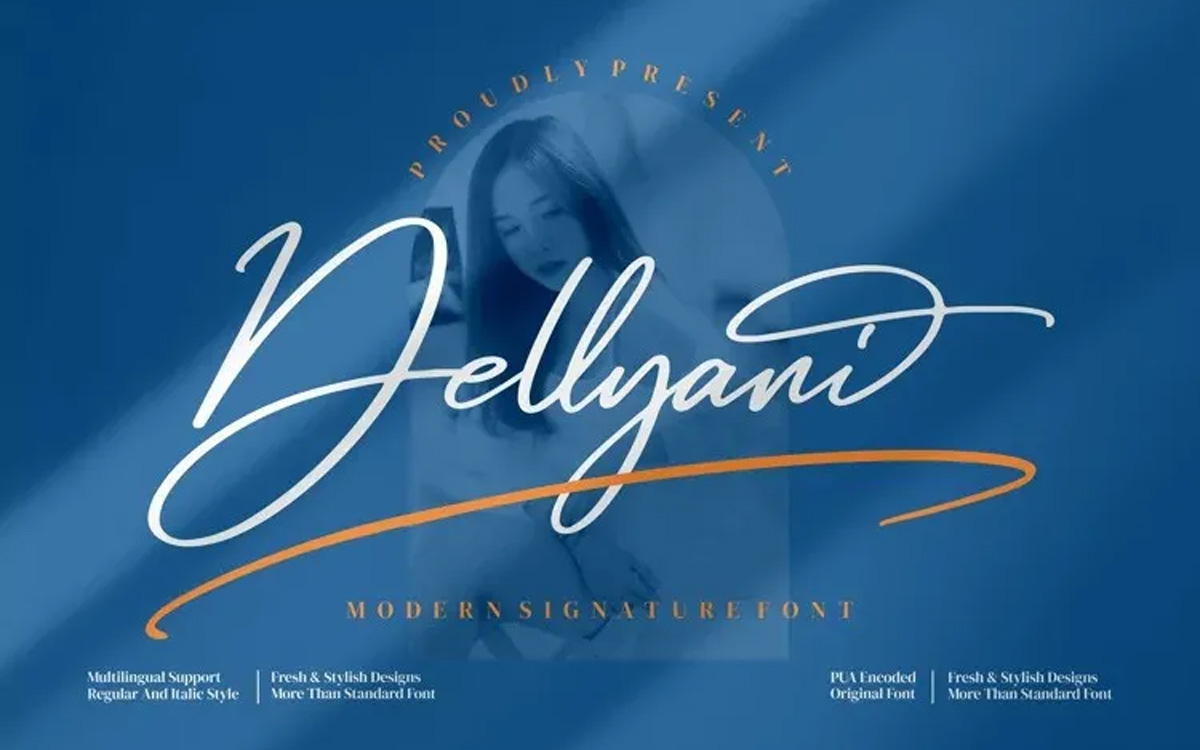
Font TH Dellyani – Nét Chữ Ký Viết Tay Mềm Mại Hoàn Hảo Cho Thiệp Cưới
Mùa cưới đang đến gần, và nếu bạn đang tìm kiếm một phông chữ mang đậm chất lãng mạn, tinh tế để tô điểm cho ngày trọng đại, thì TH Dellyani chính là sự lựa chọn không thể bỏ qua.
Thuộc dòng font script viết tay mang phong cách chữ ký (signature), TH Dellyani gây ấn tượng ngay từ cái nhìn đầu tiên bởi những đường nét uyển chuyển, bay bổng và vô cùng tự nhiên.
Những điểm nổi bật của TH Dellyani:
• Mềm mại & Tự nhiên: Từng con chữ được thiết kế tỉ mỉ để tạo cảm giác như nét mực thật lướt trên giấy, mang lại sự gần gũi nhưng không kém phần sang trọng.
• Phong cách Chữ ký Đặc trưng: Rất phù hợp để tạo điểm nhấn tên cô dâu – chú rể trên thiệp mời, giúp thiết kế trở nên cá nhân hóa và độc đáo.
• Dễ dàng kết hợp: TH Dellyani kết hợp cực kỳ ăn ý với các font Serif (có chân) hoặc Sans-Serif (không chân) tối giản, tạo nên một bố cục thiệp cưới hiện đại, thanh lịch.
Ứng dụng tuyệt vời nhất:
• Thiết kế thiệp cưới, Save The Date, menu tiệc cưới.
• Làm typography cho album ảnh cưới, photobook.
• Thiết kế logo thương hiệu, watermark cho nhiếp ảnh gia.
• Trích dẫn (quote) lãng mạn trên mạng xã hội.